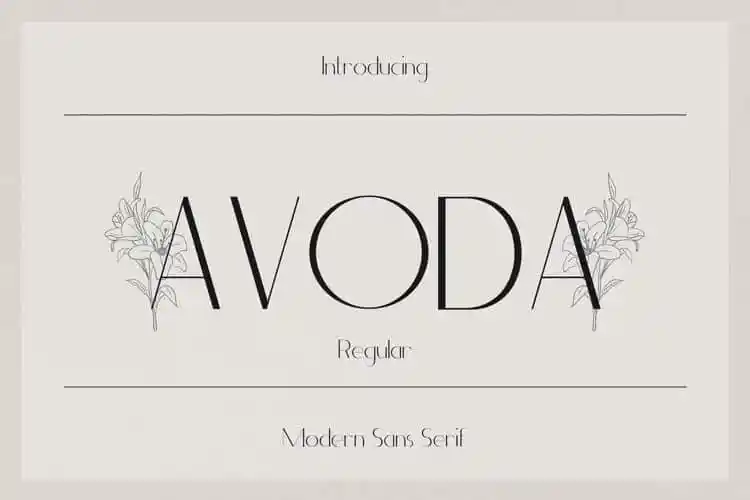
Avoda Sans Serif é uma fonte sans serif que oferece uma sensação leve e elegante ao mesmo tempo. Com suas curvas sutis que se entrelaçam suavemente em cada letra, a fonte acaba por ser algo único na categoria. Esta fonte inclui todas as letras maiúsculas e minúsculas, números e pontuação, além de suporte multilíngue – tornando-a uma invaluable adição para seu catálogo de fonts. Independentemente do assunto ou projeto, Avoda garante ser um verdadeiro ativo em qualquer criação. Seja você designer gráfico ou web designer, esta fonte certamente será o complemento perfeito para suas necessidades criativas, dando vida a qualquer projeto que precise de uma tipografia assertiva e moderna.